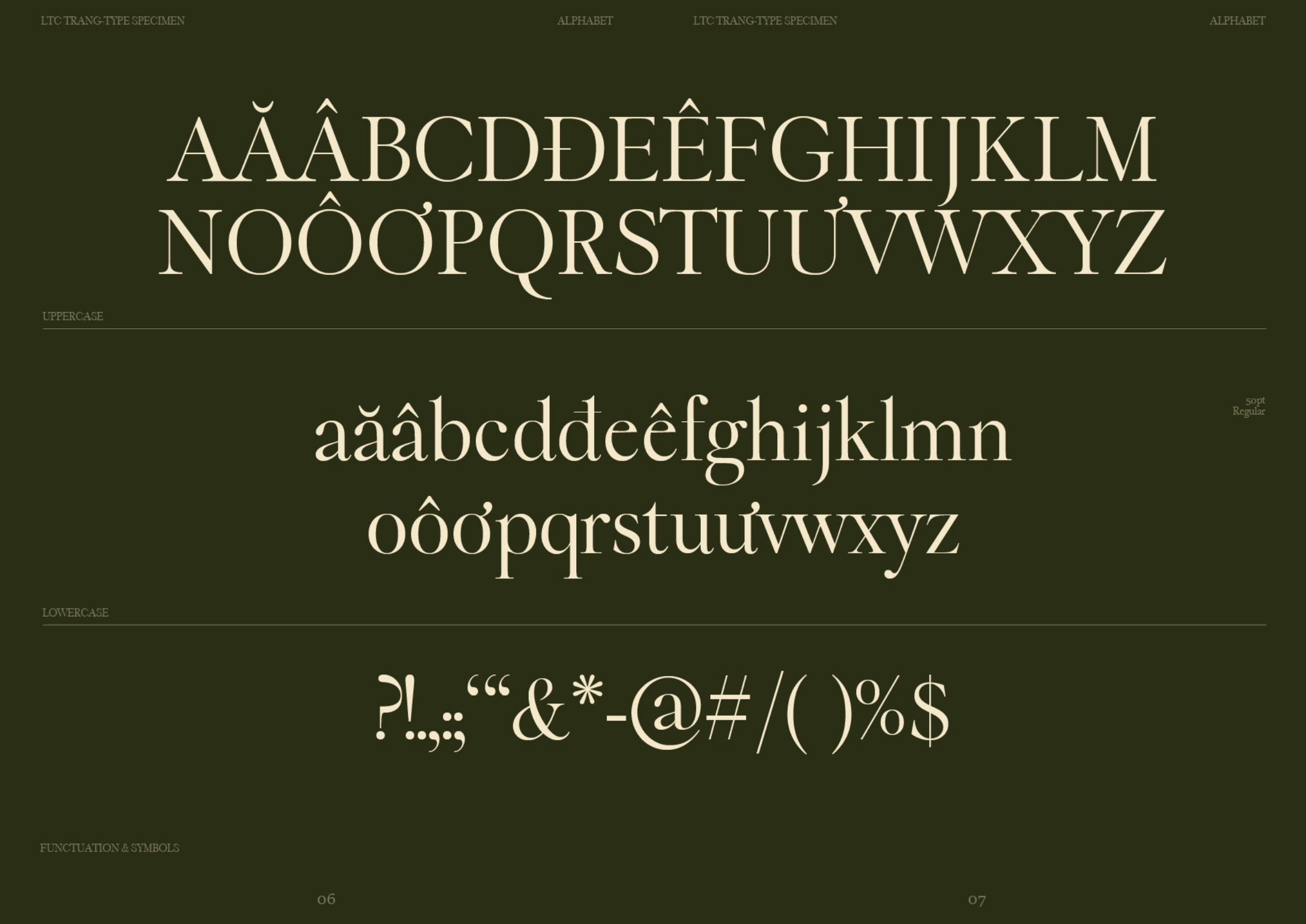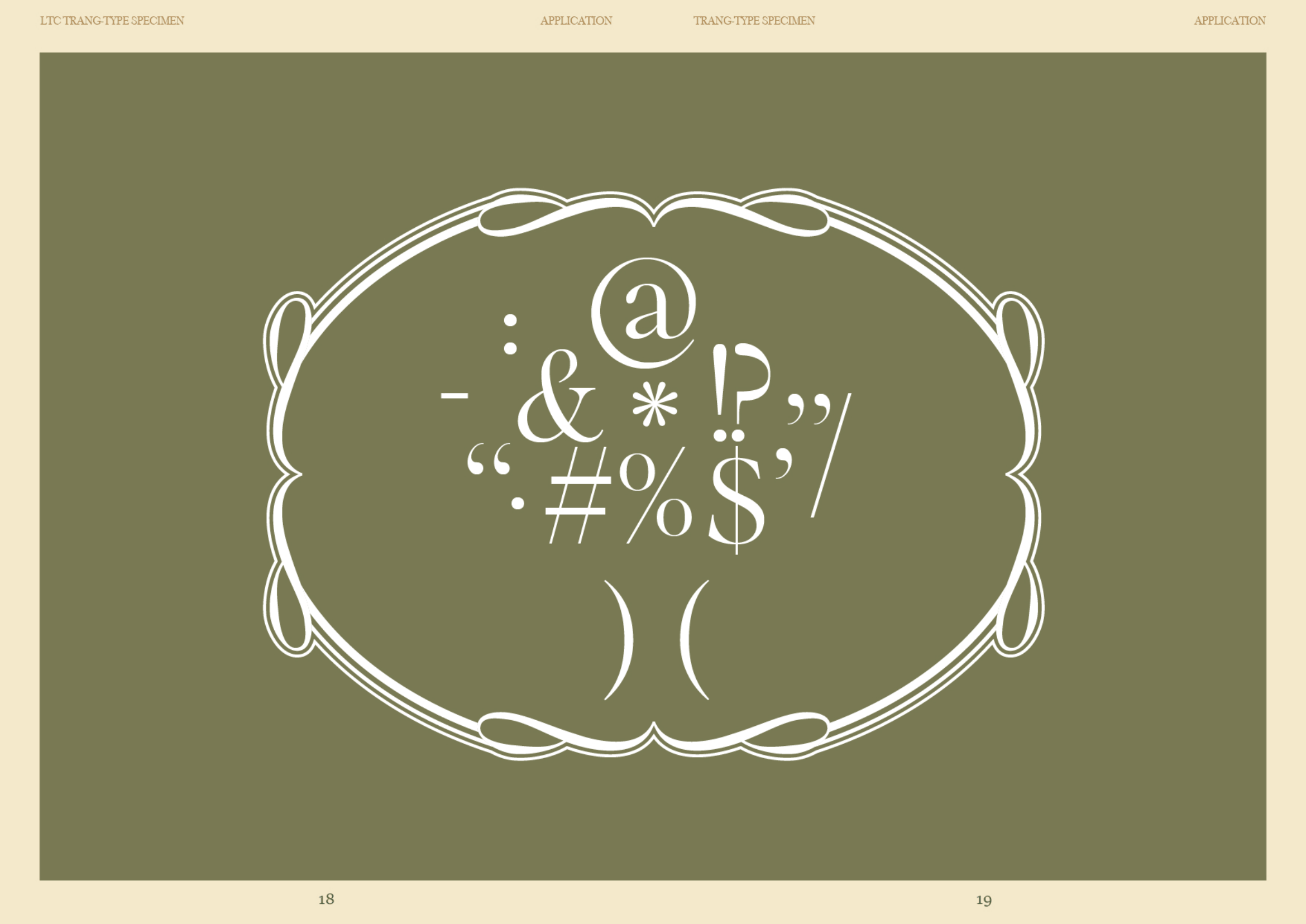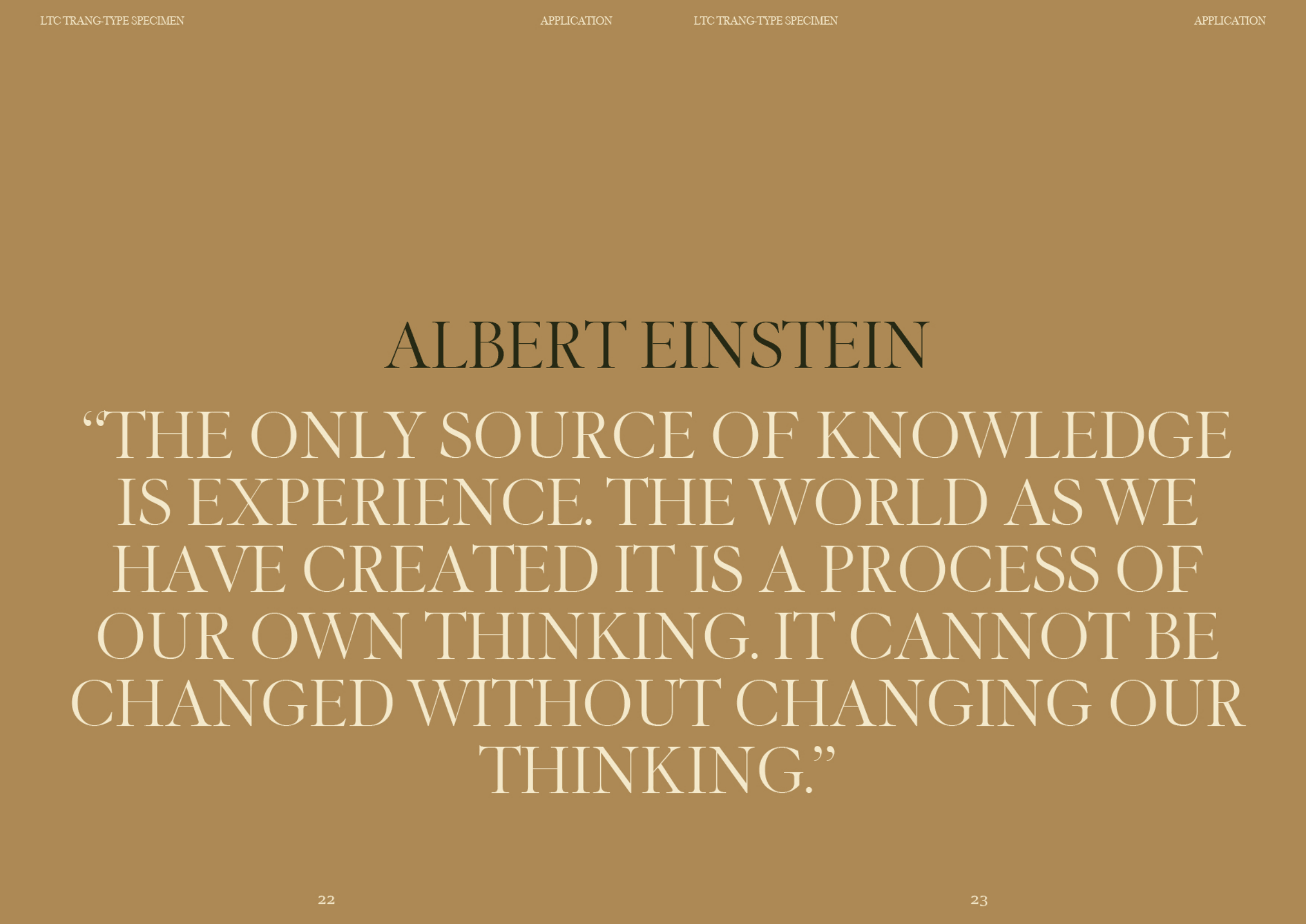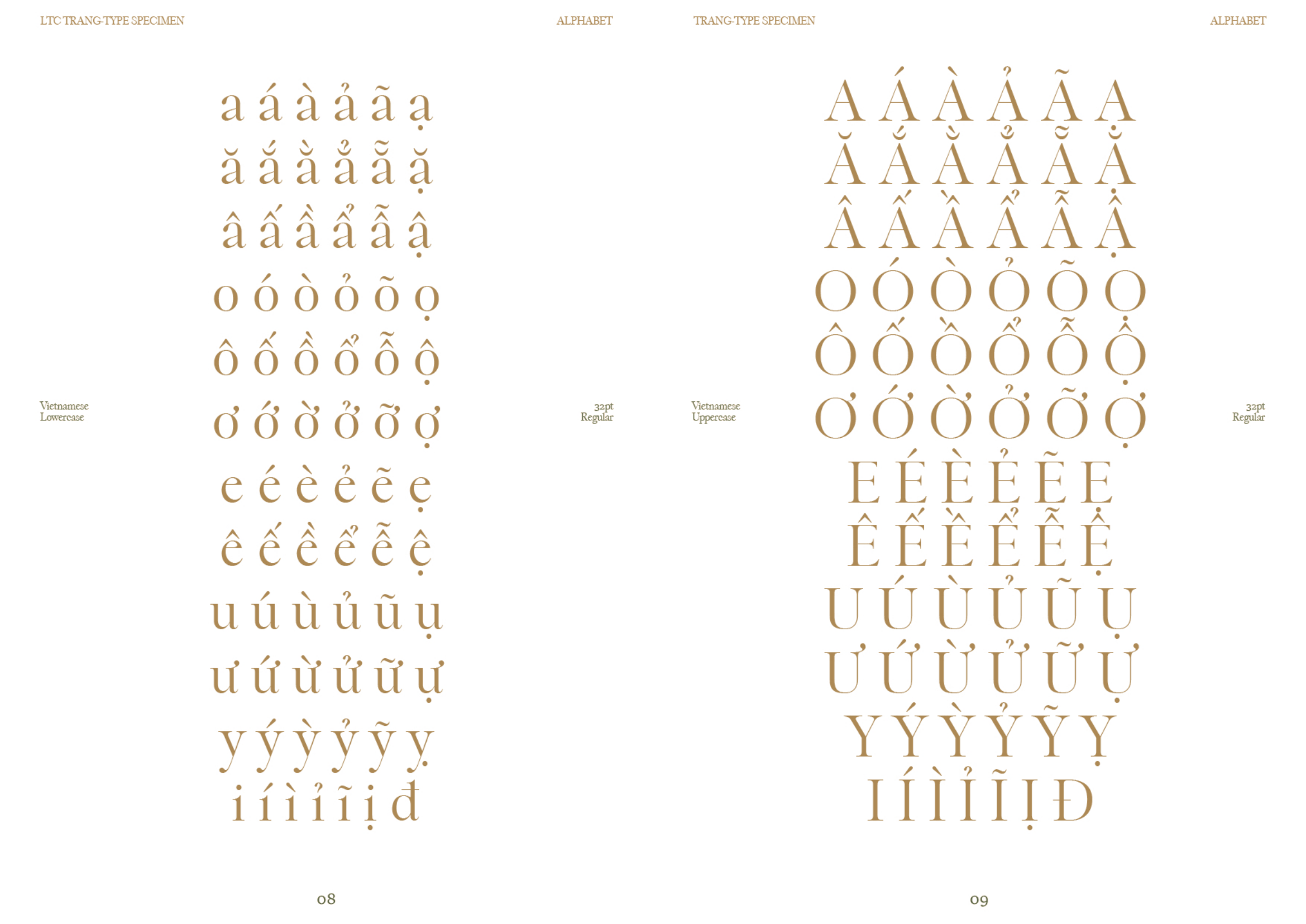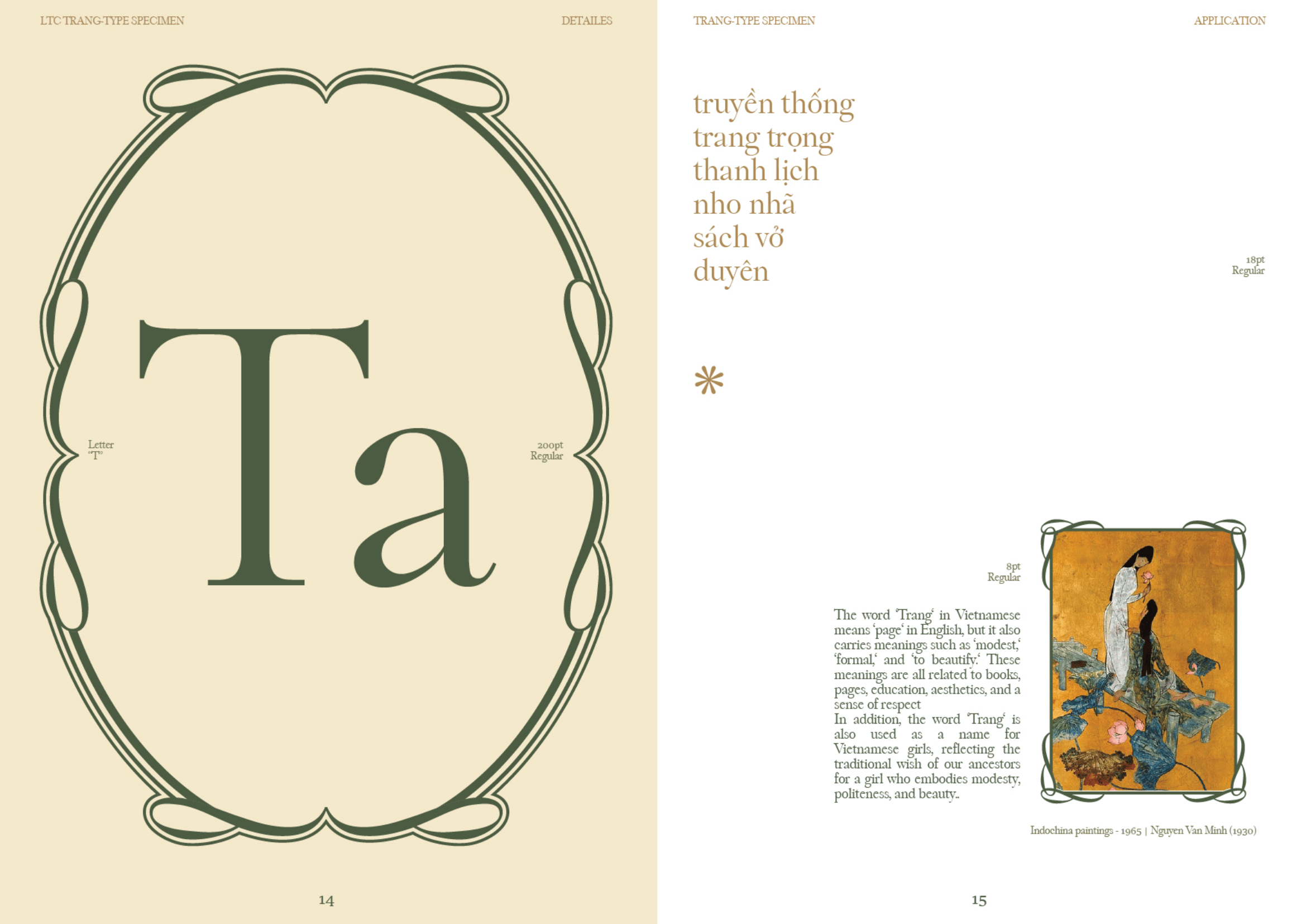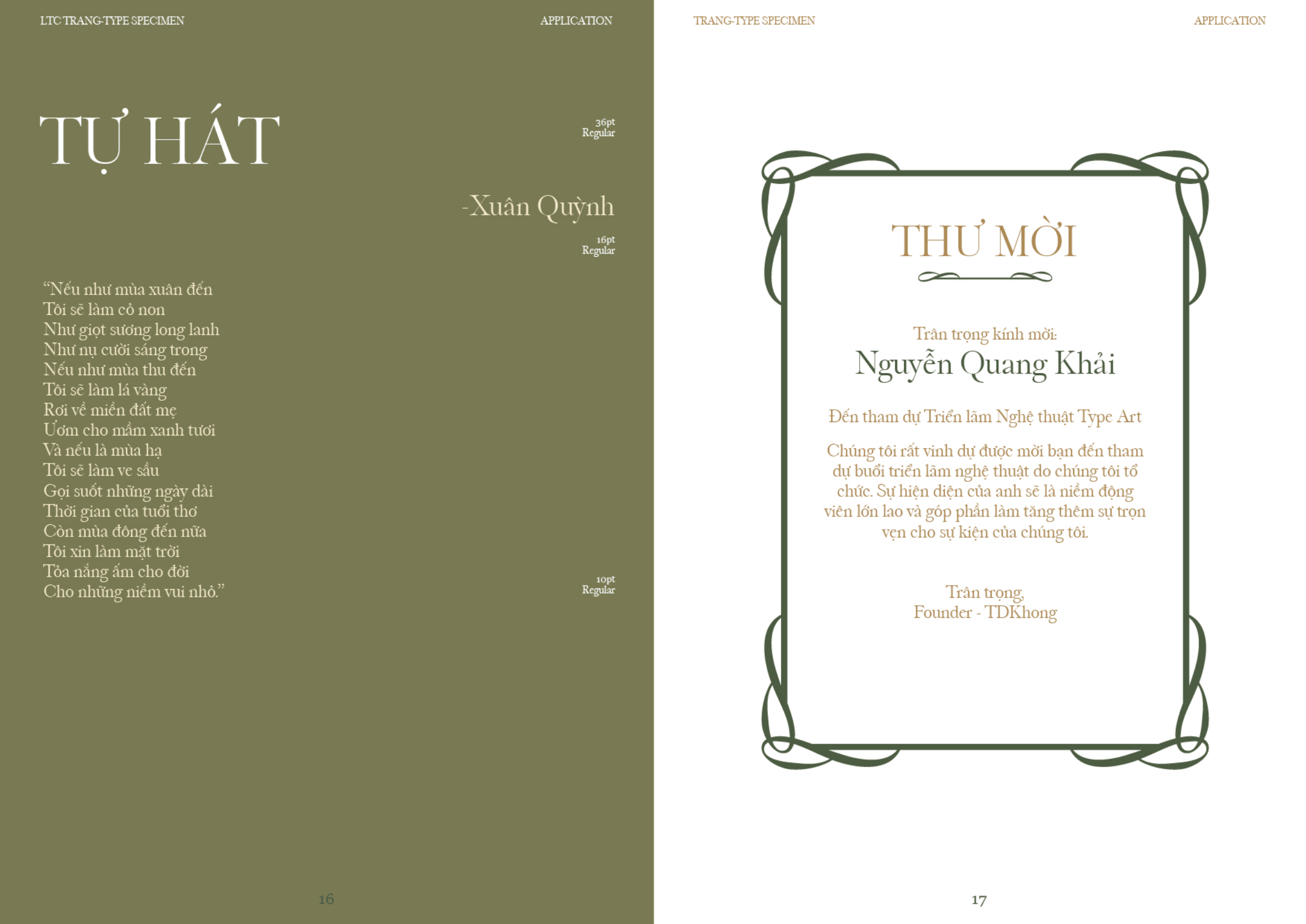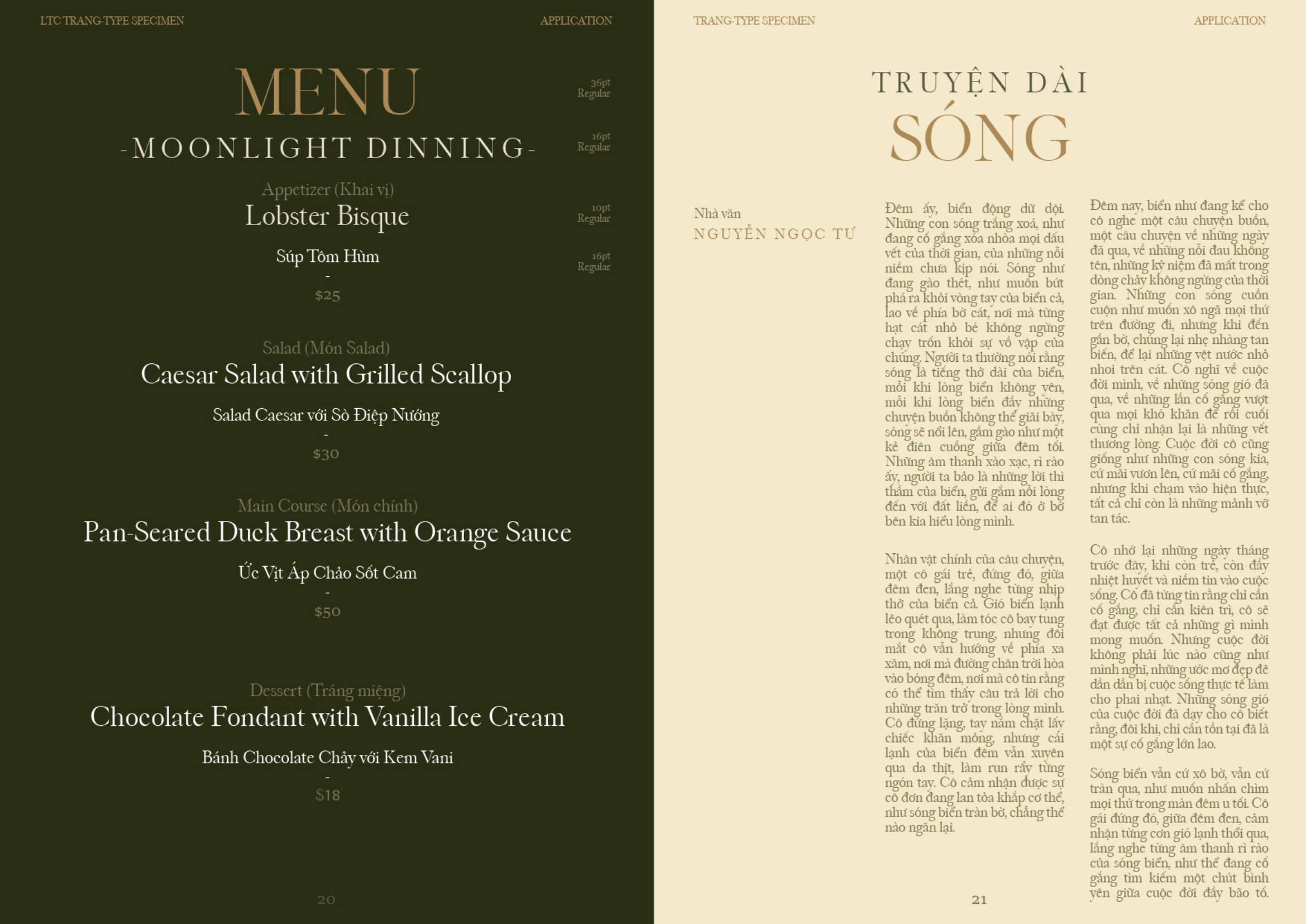
LTC Trang
Về LTC Trang: LTC Trang thuộc dòng Old Style Serif, cắp sách học theo đại diện tiêu biểu nhất là Granjon của Linotype. LTC Trang có vóc dáng thanh mảnh, yêu kiều phù hợp cả tiêu đề và văn bản dài.
Old Style Serif
Text
LTC Trang
Granjon is a serif typeface designed in 1928 by George W. Jones for the Linotype foundry, inspired by the work of the 16th-century punchcutter Robert Granjon. Unlike strict historical revivals, Granjon is an interpretation of Renaissance old-style typography, particularly influenced by Granjon’s expressive italics, which are a defining feature of the typeface.
LTC Trang
The design combines classical proportions with a warm, calligraphic rhythm, visible in its gently bracketed serifs, moderate contrast, and flowing italic forms that retain a strong sense of handwriting. Originally intended for book typography, Granjon offers good readability in continuous text while also carrying a refined, literary tone. Its italics are especially notable for their elegance and liveliness, often considered among the most successful revivals of Renaissance cursive writing in metal type. Overall, Granjon stands as a 20th-century reinterpretation of humanist printing traditions, balancing historical reference with the technical and aesthetic needs of modern typesetting.